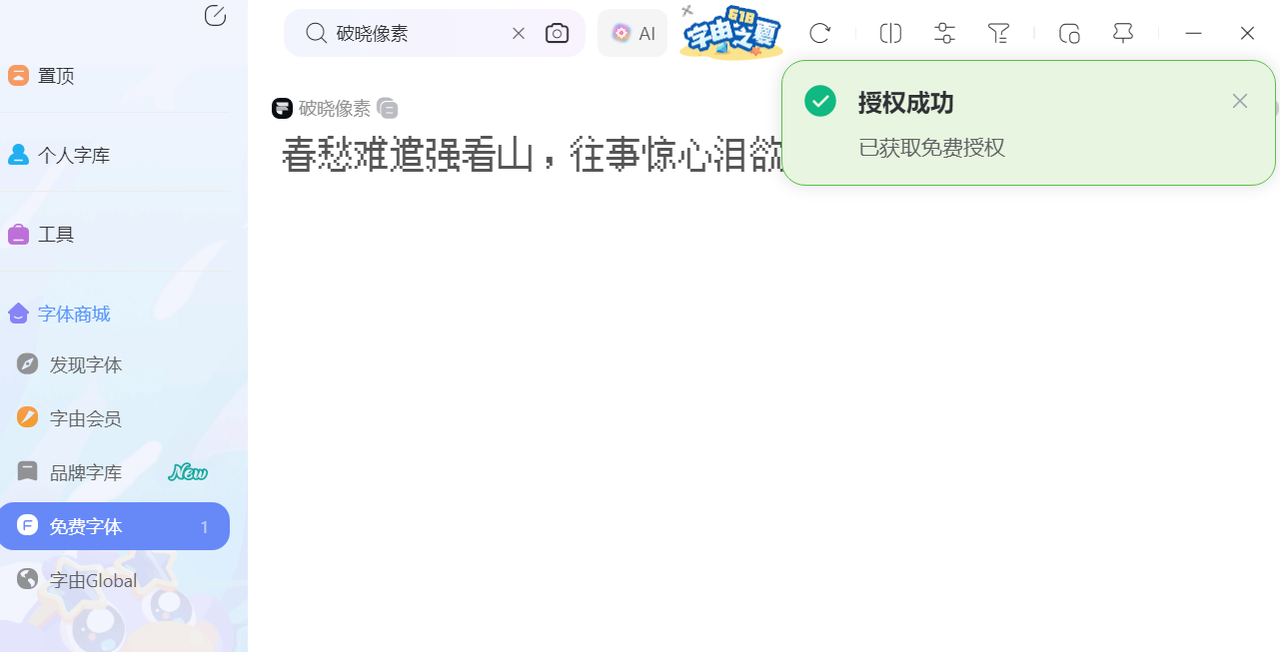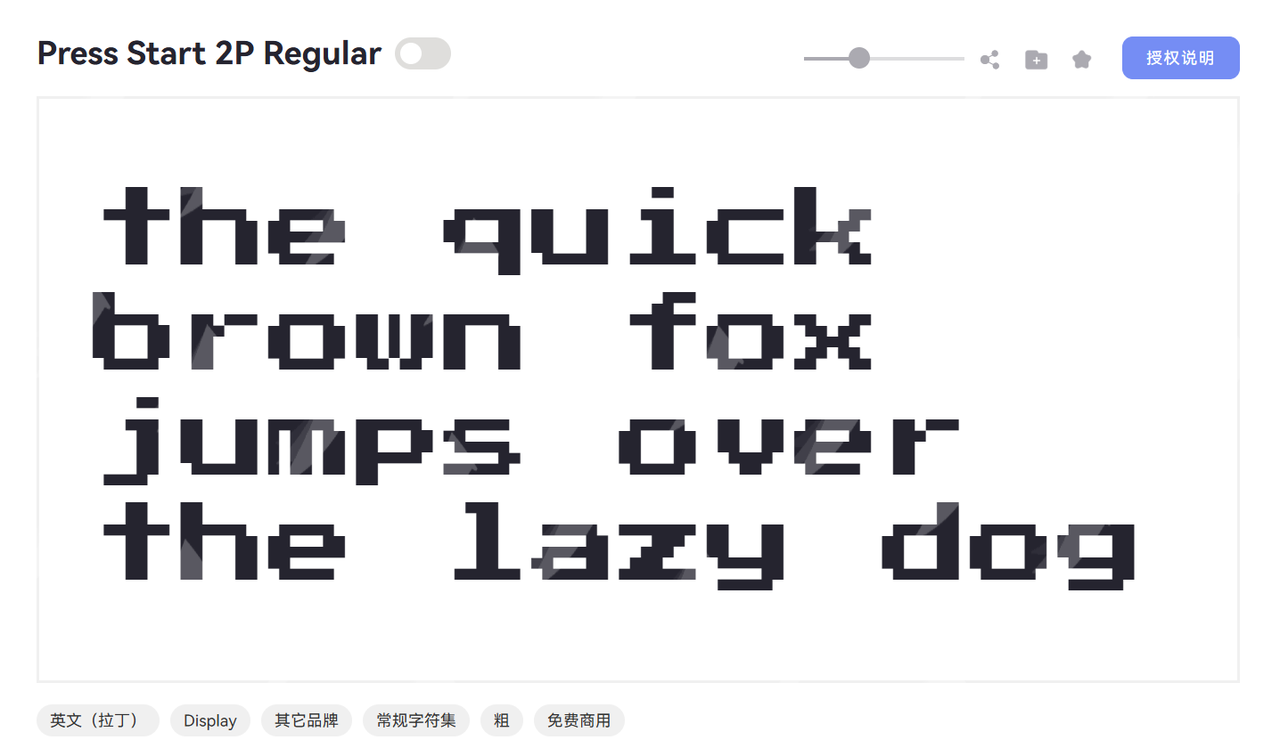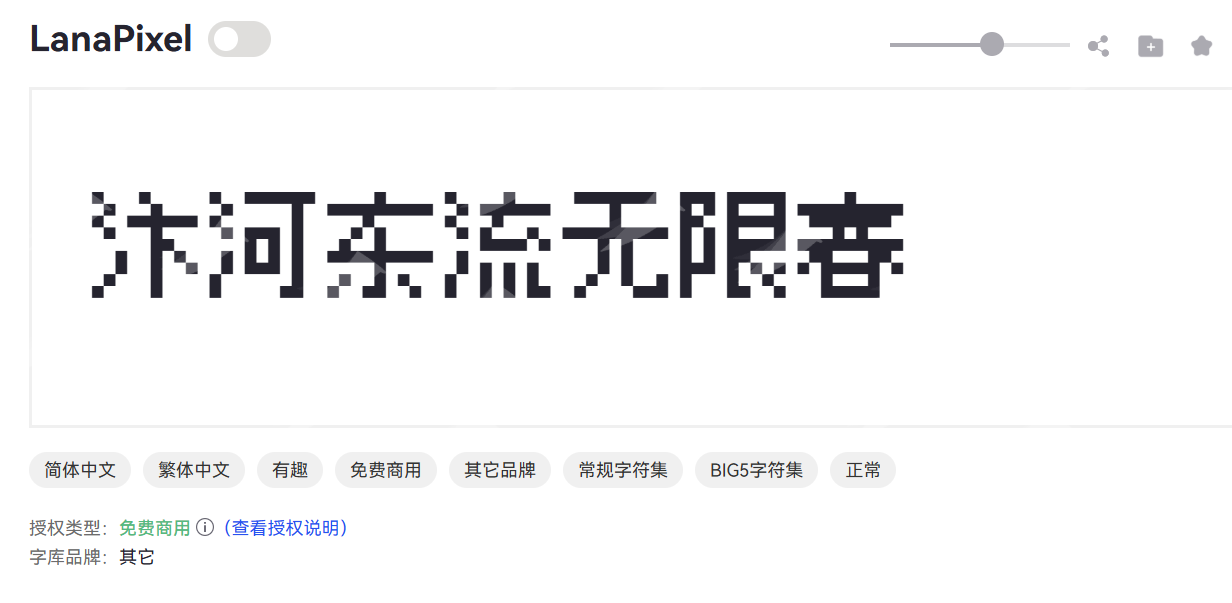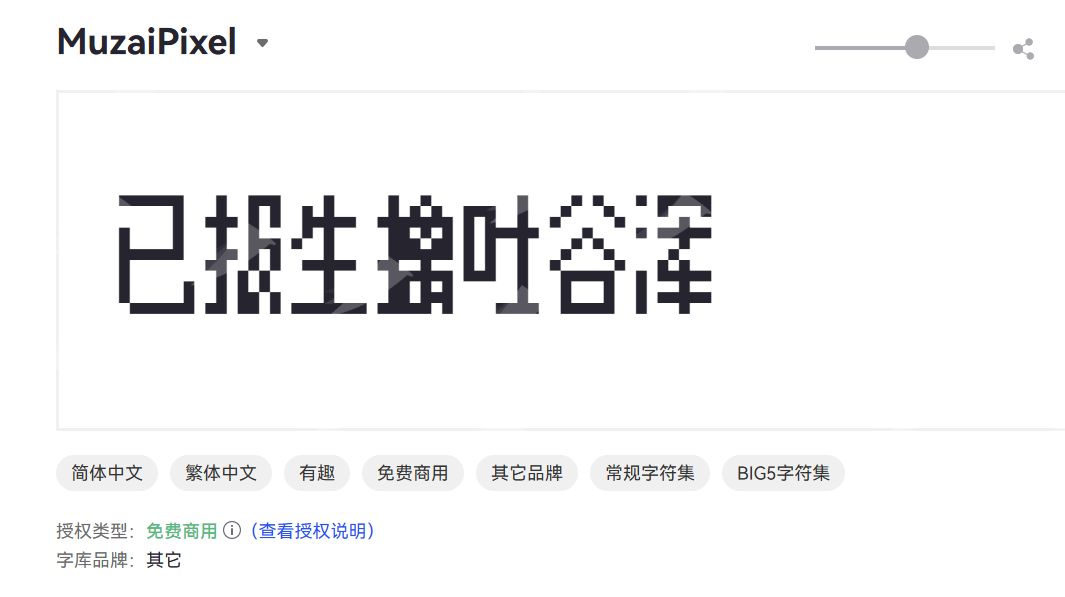
在做设计或者创作项目时,我经常遇到一个困扰:既想要有特色的像素风字体,又希望这些字体能够免费且允许商用,免去版权纠纷的担忧。像素字体因其独特的复古与艺术感在游戏界面、广告海报、电子产品界面等领域非常流行,但找到合适且合法可用的免费商用像素字体并非易事。
一、经典复古风
Press Start 2P
Press Start 2P字体灵感源自80年代街机游戏的像素艺术,笔画分明,字符方正,极具怀旧味道。
适合用于游戏UI设计、复古风海报、网站标题或任何想唤起怀旧感的数字作品。
PixelMplus
PixelMplus 是经典复古像素等宽字体,点阵轮廓清晰规整,包含中日英多字符集,像素颗粒干净利落,复古游戏氛围感强烈。字符间距均匀,显示清晰无模糊,适配像素风插画、复古游戏界面、数码海报、怀旧短视频字幕等设计。
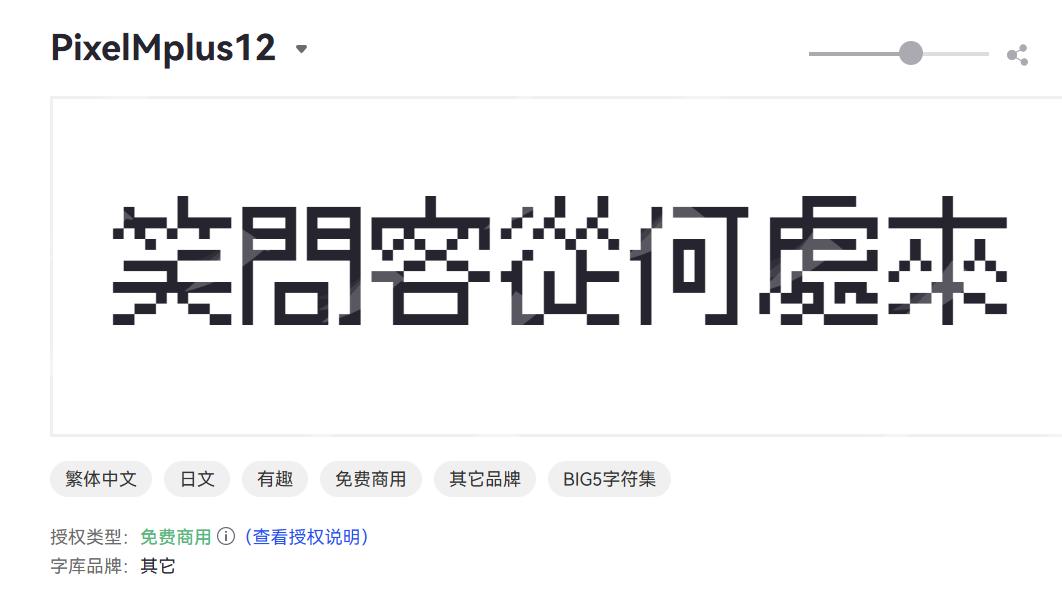
二、现代简约像素风
LanaPixel
LanaPixel拥有简洁硬朗的像素字形,色块分布均匀,提供多种字体粗细。非常适合电子游戏内的界面文字、应用程序、甚至电子产品包装上的风格字体。
破晓像素
破晓像素是一款清爽的点阵中文字体,像素线条利落干净,字形方正匀称,字符覆盖汉字、数字与英文。整体风格简约怀旧,辨识度高,自带早期电子屏幕氛围感。适配像素游戏界面、复古数码海报、二次元短视频字幕、像素风文创设计。
三、可爱风像素字体
MuzaiPixel
MuzaiPixel 是国产可爱风像素中文字体,点阵柔和圆润,字形小巧饱满,兼顾汉字、字母与数字完整字符集。像素颗粒柔和不生硬,复古童趣氛围浓厚,可读性佳。适合像素风插画、游戏 UI、二次元海报、短视频像素字幕等创作。
莫妮卡像素圆体
莫妮卡像素圆体的设计灵感源自游戏Minecraft,字体轮廓圆润可爱,视觉风格活泼生动。非常适合儿童教育类APP、动画栏目、儿童读物封面设计,亦可用于趣味性强的社交媒体账号元素。